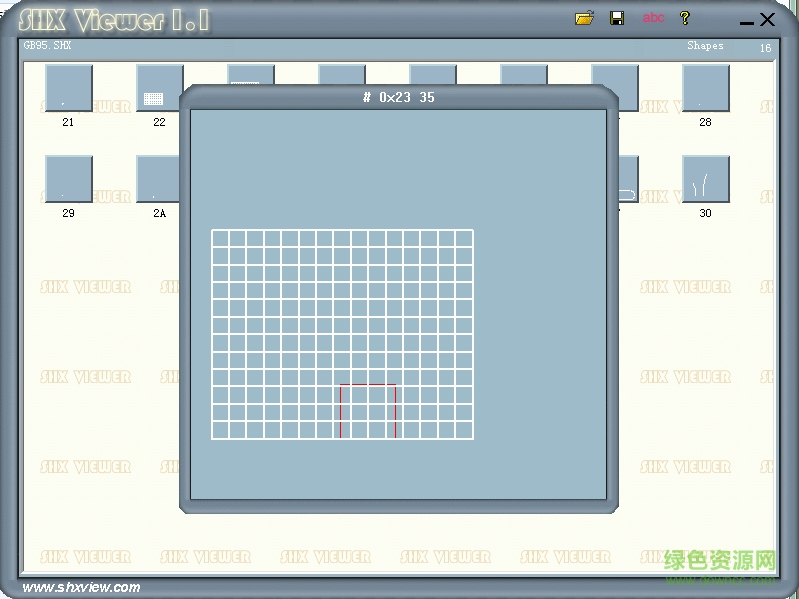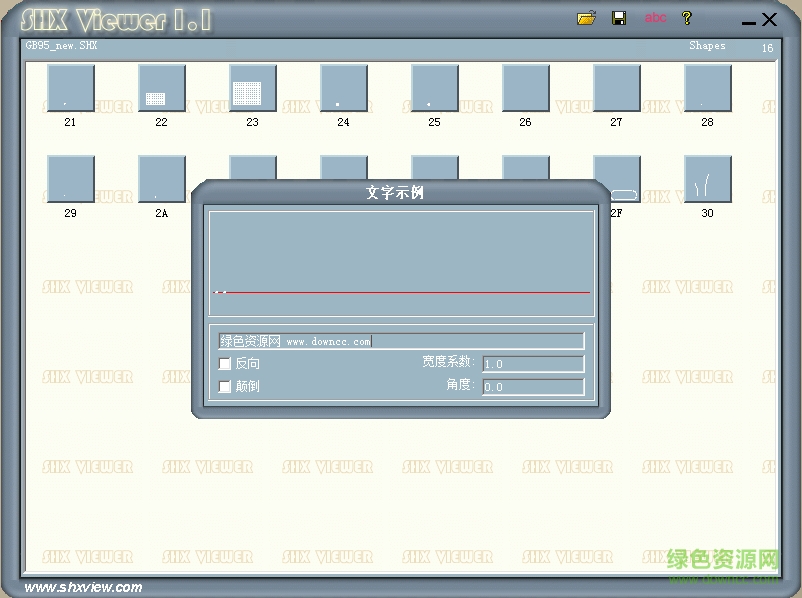
gb95 new.shx是一款形字體文件的cad字體,僅有16個(gè)字符,可用于平面設(shè)計(jì)中的標(biāo)記描點(diǎn)等,其前身是gb95.shx,如果你有需要來(lái)綠色資源網(wǎng)即可下載!
gb95 new.shx并不是標(biāo)準(zhǔn)字體,是圖紙所有者所有的特殊字體,應(yīng)該是GB95.shx改名稱的字體,GB95.shx本身是一款shapes字體,適用于autocad中的平面設(shè)計(jì)、排版印刷等場(chǎng)合。
*.shx文件在CAD里叫形文件,它分為兩種:字體文件和符號(hào)形文件;字體文件又分兩種,可以叫做小字體和大字體。
常規(guī)字體就小字體(Unifont),大字體是Bigfont,形文件就是符號(hào)形(Shapes)。
大字體是針對(duì)中文、韓文、日文等雙字節(jié)(全角)文字定制的字體文件。在文字樣式對(duì)話框中必須勾選“使用大字體”,才能在右側(cè)列表中選擇大字體文件。由于中文、日文的字符比較多,而且每個(gè)字符的定義都比較復(fù)雜,這類文件通常比較大,從幾百K到幾MB不等。
符號(hào)形中保存的是線型、公差或直接可插入到圖形中的一些符號(hào),這些文件無(wú)法在文字樣式中設(shè)置。